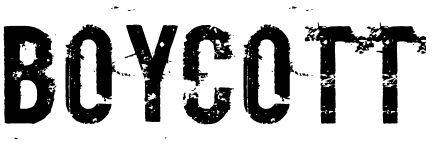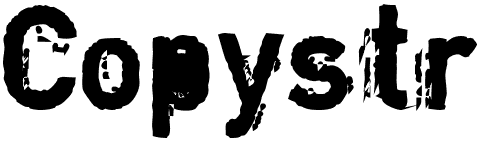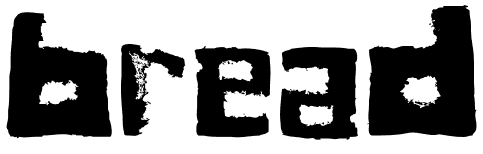
100 бесплатных абстрактных и гранжевых шрифтов
гранжевые-шрифтыЕсли вы заметили, стиль гранж и абстракция быстро занимают ведущие места в веб 2.0дизайнах. Эти грязные, абстрактные, урбанистические и состаренные элементы стали новыми фаворитами у множества дизайнеров. Если вы всё ещё придерживаетесь глянцевых и блестящих дизайнов в стиле веб 2.0, то это самое время для того чтобы перейти к новому стилю – стилю гранж.
Затёртый шрифт
Затертый шрифт
Выпуклый шрифт
Выпуклый шрифт
Крупный дырявый шрифт
Крупный дырявый шрифт
Старый шрифт
Старый шрифт
Шрифт в рокерском стиле
Шрифт в рокерском стиле
Шрифт с завитками
Шрифт с завитками
Неаккуратный шрифт
Неаккуратный шрифт
Городской скетч
Городской скетч
Полночь
Затёртый винил
Затертый винил
Рваный турбо-шрифт
Рваный турбо шрифт
Разгром
Шрифт в стиле гранж
Шрифт в стиле гранж
Беспорядочный шрифт
Беспорядочный шрифт
Гранжевый трафарет
Гранжевый трафарет
Гранжевый шрифт
Гранжевый шрифт
Шрифт в пятнах
Шрифт в пятнах
Шрифт «от руки»
Шрифт
Не чёткий шрифт
Не четкий шрифт
Размазанный шрифт
Размазанный шрифт
Королевский шрифт
Королевский шрифт
Брызги краски
Брызги краски
Сатанинские надписи
Сатанинские надписи
Шрифт из металлических элементов
Шрифт из металлических элементов
Бесплатный гранжевый шрифт
Бесплатный гранжевый шрифт
Рассыпанный шрифт
Рассыпанный шрифт
Разбитый шрифт
Разбитый шрифт
Потёртый шрифт
Потертый шрифт
Текст с разрывами
Текст с разрывами
Размазанные буквы
Размазанные буквы
Плохо отпечатанный шрифт
Плохо отпечатанный шрифт
Гранжевая надпись
Гранжевая надпись
Состаренный шрифт
Состаренный шрифт
Жирный шрифт в стиле гранж
Жирный шрифт в стиле гранж
Отпечаток
Кривой шрифт
Кривой шрифт
Хэллоуинский текст
Хэллоуинский текст
Округлённый шрифт
Округленный шрифт
Обведённый шрифт
Обведенный шрифт
Нарисованный шрифт
Нарисованный шрифт
Потрескавшийся шрифт
Потрескавшийся шрифт
Шрифт с отпечатками
Шрифт с отпечатками
Кривой шрифт
Кривой шрифт
Шрифт в потёках
Шрифт в потеках
Ровный тонкий шрифт
Ровный тонкий шрифт
Шрифт-роспись
Размазанный шрифт
Размазанный шрифт
Печатный гранжевый шрифт
Печатный гранжевый шрифт
Художественный шрифт
Художественный шрифт
Шрифт с потёками
Шрифт с потеками
Разнообразный шрифт
Разнообразный шрифт
Старый рыцарский шрифт
Старый рыцарский шрифт
Полосатый шрифт
Полосатый шрифт
Почёрканный шрифт
Почерканный шрифт
Заштрихованный шрифт
Заштрихованный шрифт
Шрифт с завитками
Шрифт с завитками
Размытый шрифт
Размытый шрифт
Старинный шрифт
Старинный шрифт
Протёртый шрифт
Протертый шрифт
Шрифт-рисунок
Шрифт в клеточку
Шрифт в клеточку
Кривой шрифт «от руки»
Кривой шрифт
Крупный трафаретный шрифт
Крупный трафаретный шрифт
Шрифт в потёках и брызгах
Шрифт в потеках и брызгах
Мистический шрифт
Мистический шрифт
Зарисованный шрифт
Зарисованный шрифт
Шрифт на бумаге
Шрифт на бумаге
Необычный шрифт
Необычный шрифт
Ретро шрифт
Ретро шрифт
Размазанные чернила
Размазанные чернила
Затёртая надпись
Затертая надпись
Наброски
Размазня
Затёртая надпись
Затертая надпись
Буквы различного размера
Разноразмерные буквы
Крупный грнжевый шрифт
Крупный грнжевый шрифт
Угловатый шрифт
Угловатый шрифт
Размазанная надпись
Размазанная надпись
Грязный шрифт
Грязный шрифт
Грязный шрифт с потёками
Грязный шрифт с потеками
Разрисованный шрифт
Разрисованный шрифт
Старый затёртый шрифт
Старый затертый шрифт
Поцарапанный шрифт
Поцарапанный шрифт
Разрушенный шрифт
Разрушенный шрифт
Тяжёлый грязный шрифт
Тяжелый грязный шрифт
Испорченный шрифт
Испорченный шрифт
Ретро шрифт
Ретро шрифт
Дырявый шрифт
Дырявый шрифт
Не аккуратный размазанный шрифт
Не аккуратный размазанный шрифт
Надпись на газетном листе
Надпись на газетном листе
Ретро завитки
Ретро завитки
Не дорисованный шрифт
Не дорисованный шрифт